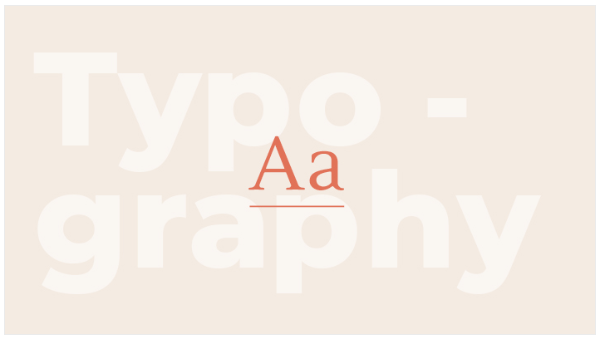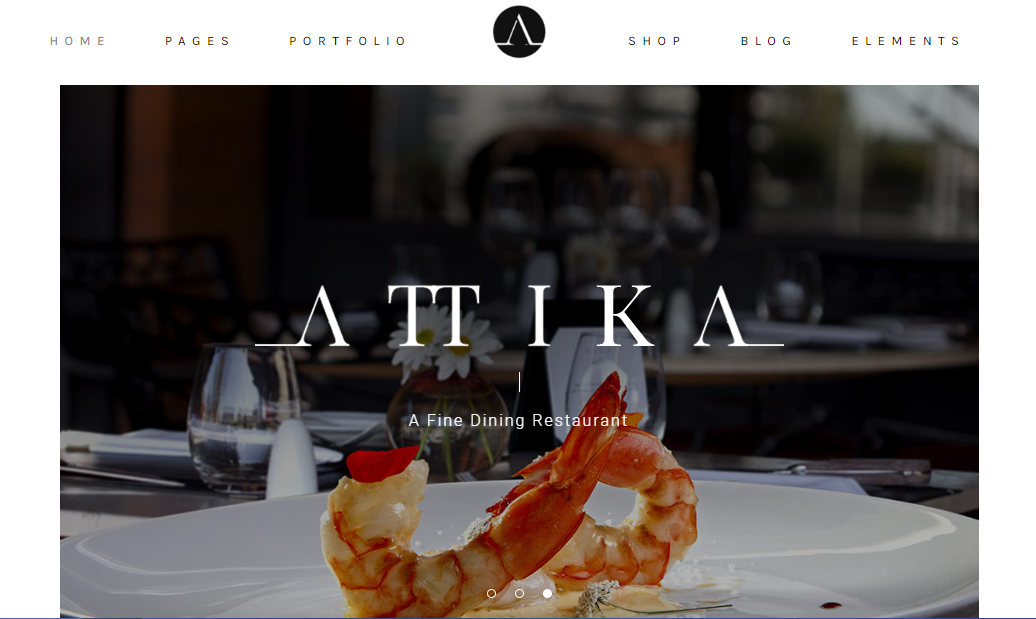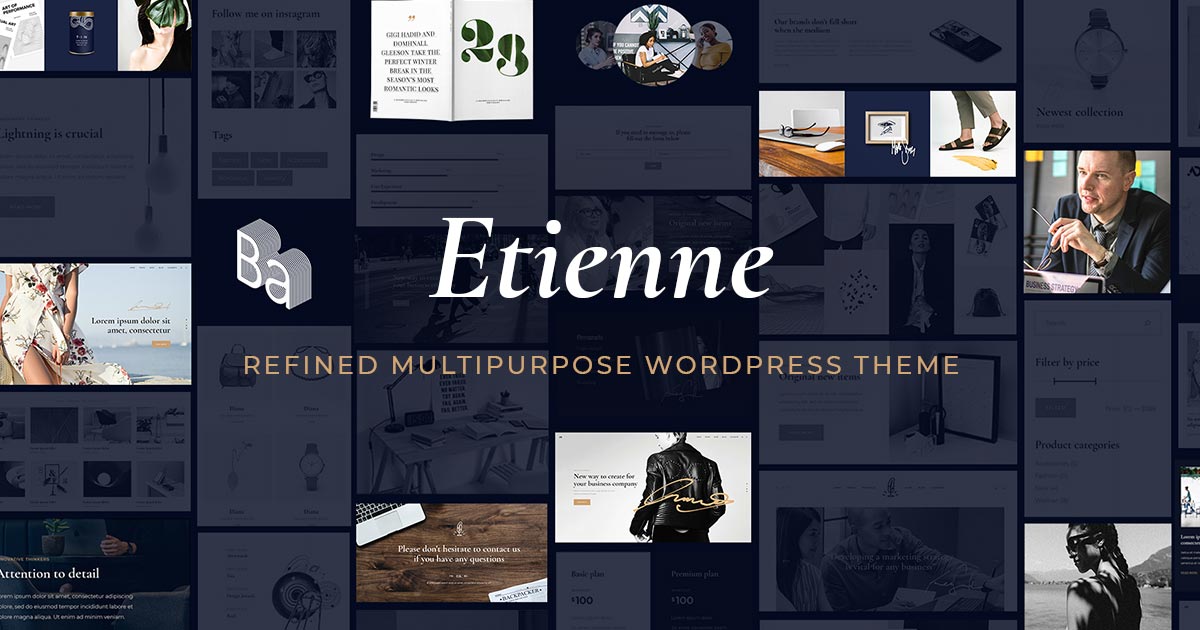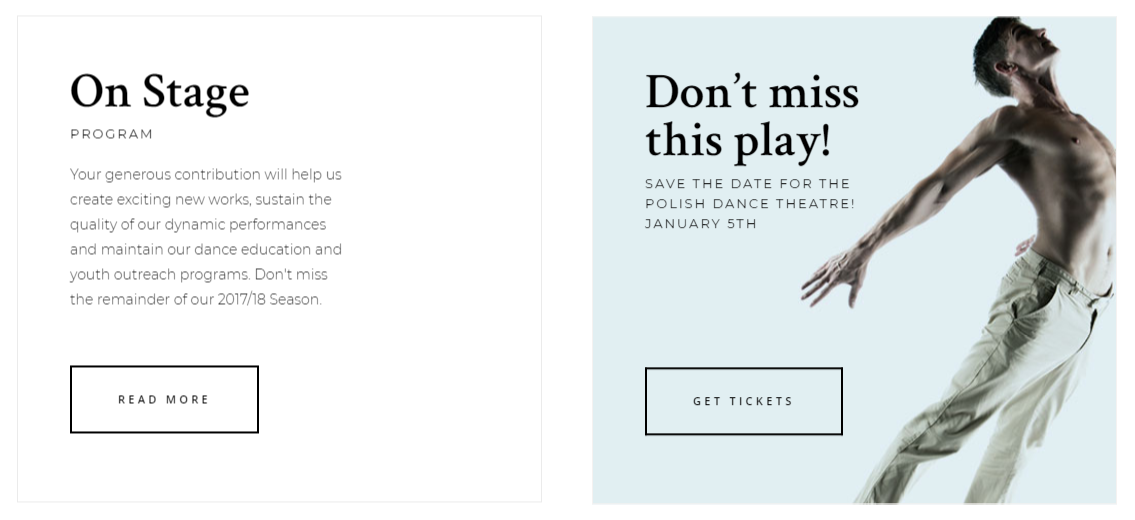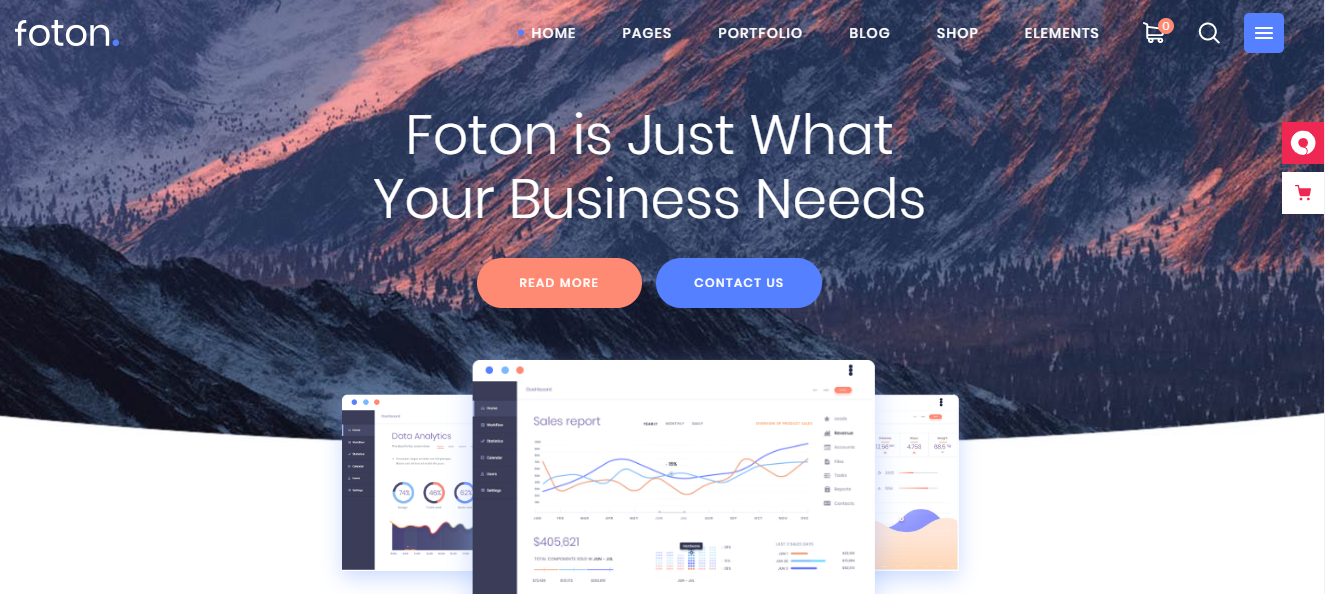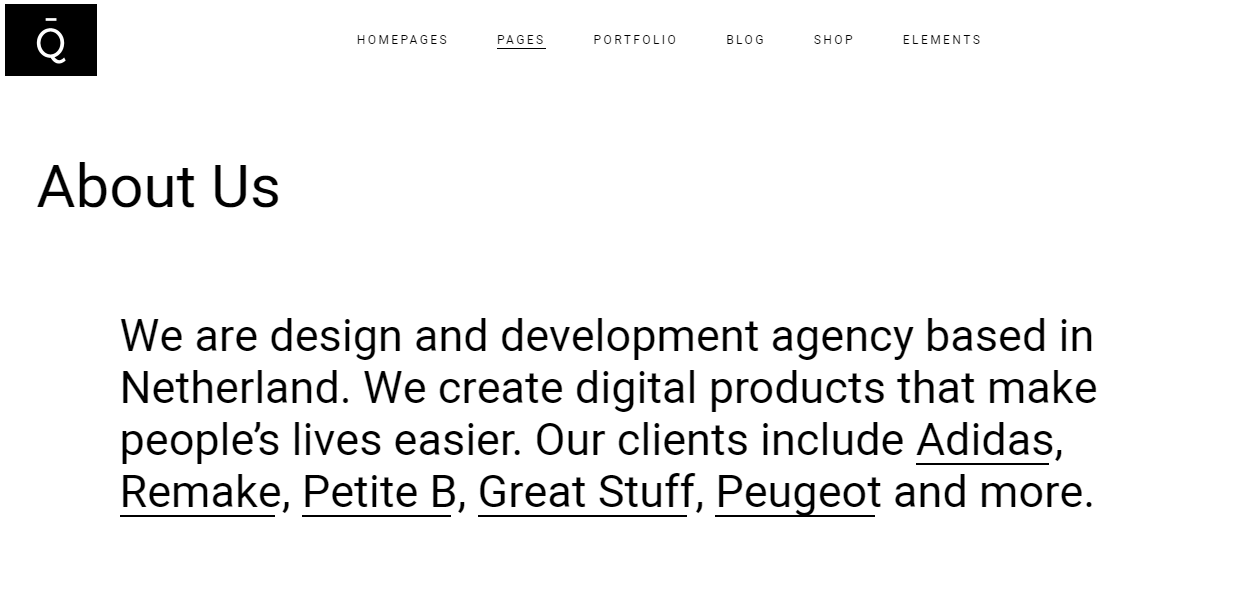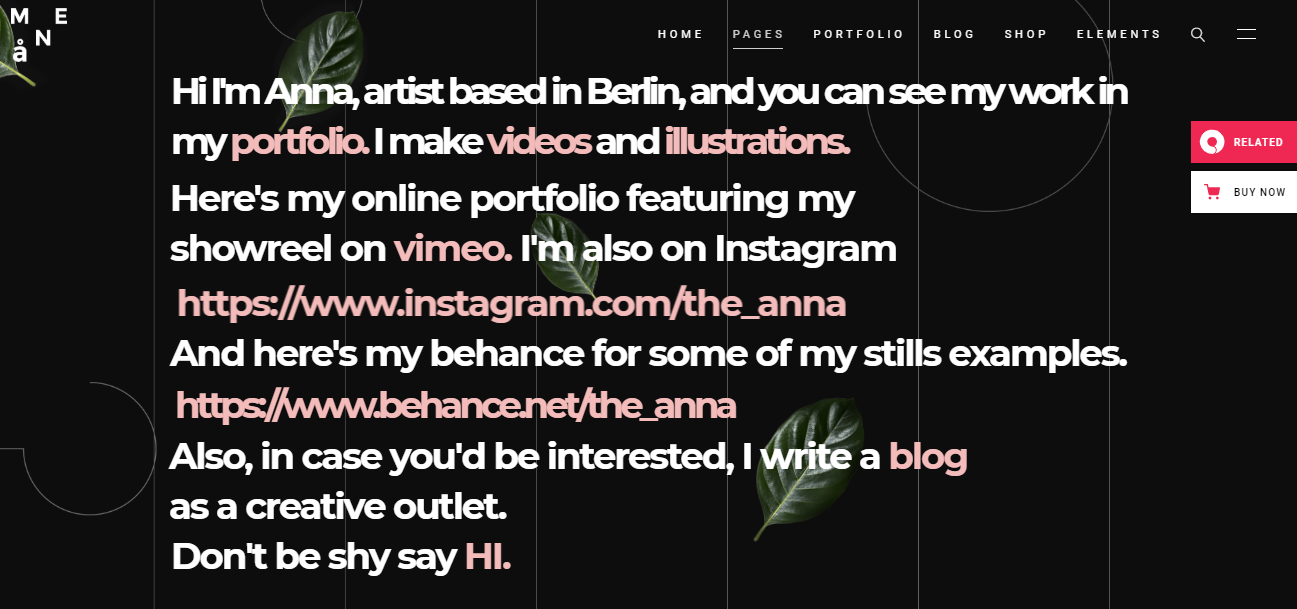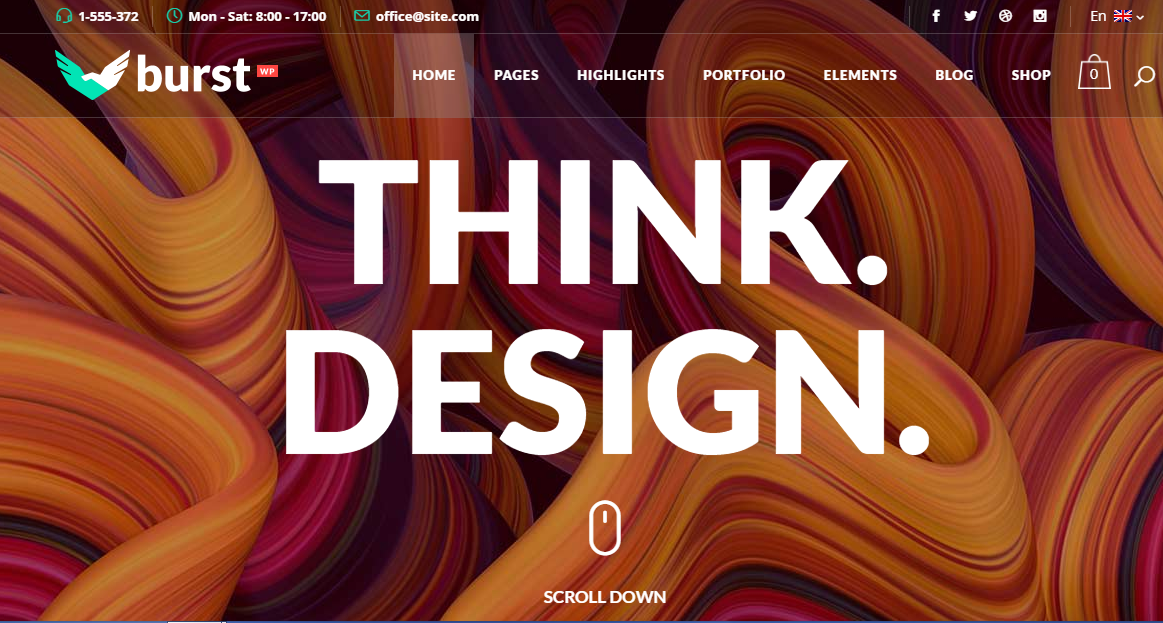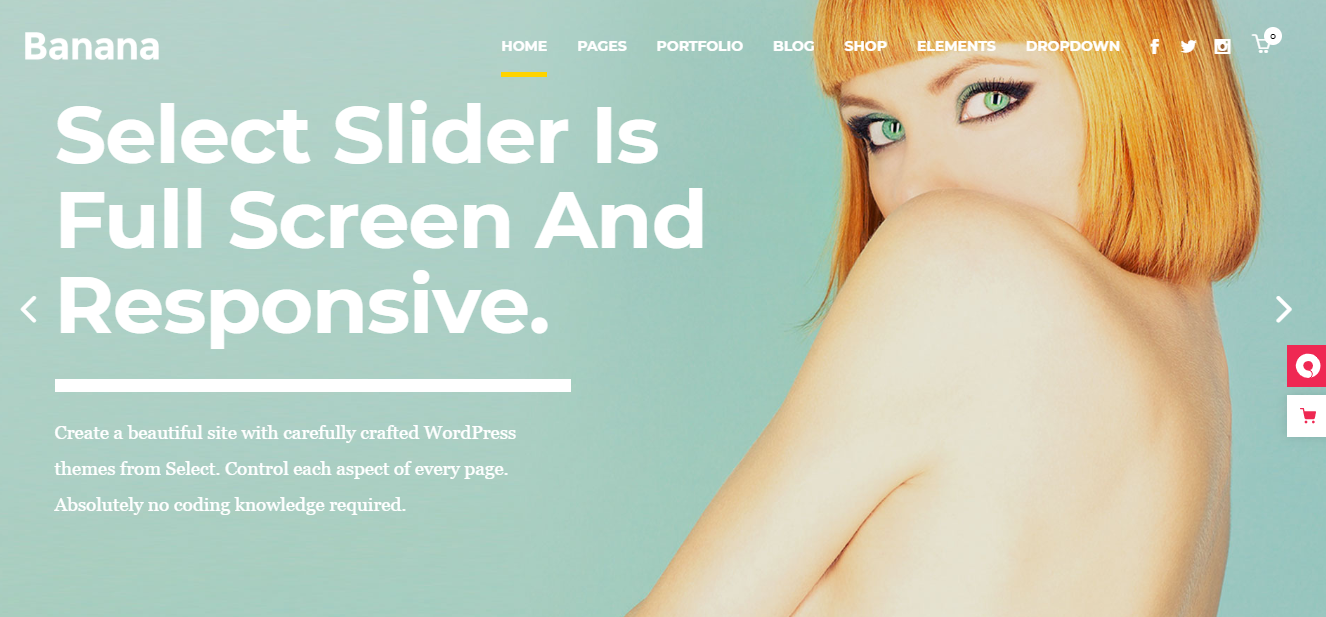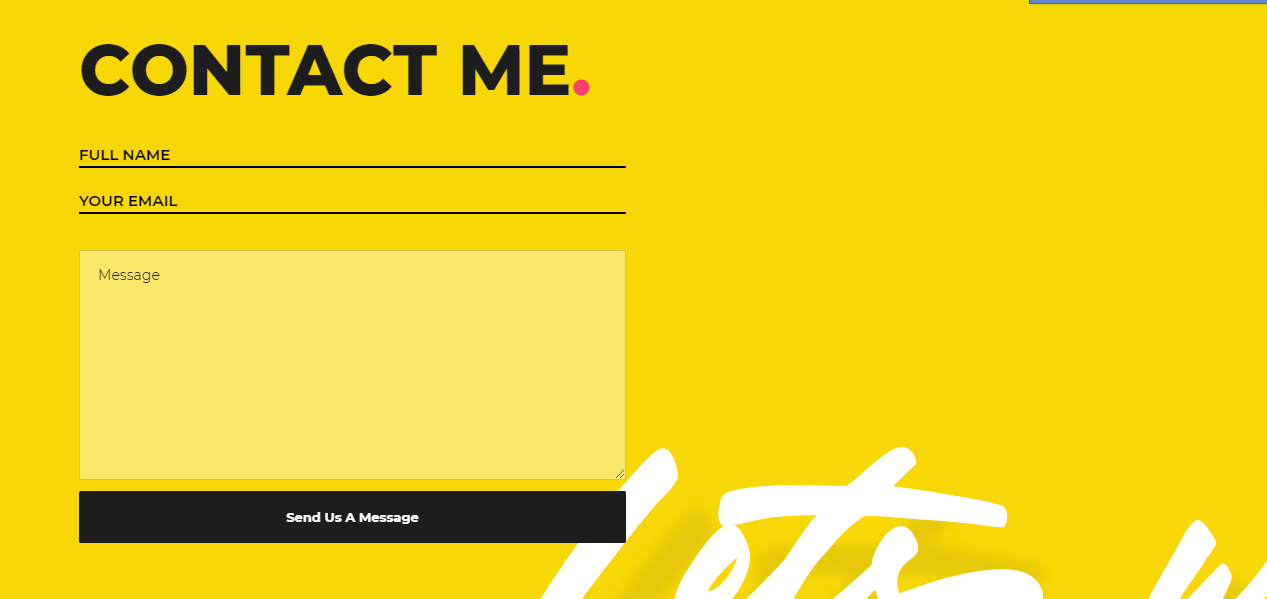
6 mẹo lựa chọn font chữ cho thiết kế website hoàn hảo năm 2024
Lựa chọn font chữ cho thiết kế website ấn tượng chưa bao giờ là dễ dàng. Lựa chọn font chữ là yếu tố quyết định tới tính thẩm mỹ của một thiết kế website. Nếu bạn đang gặp khó khăn trong việc thiết kế website, hãy tham khảo 6 mẹo lựa chọn font chữ cho thiết kế website hoàn hảo cùng Bee Art nhé!
Thiết kế website là một quá trình dài hơi cần bỏ ra nhiều công sức. Bạn phải cân nhắc nhiều yếu tố, từ cách phối màu đến xác định vị trí logo, bố cục và thiết kế nội dung văn bản. Có lẽ phần khó khăn nhất khi thiết kế website chính là làm cách nào để phối hợp thật tốt tất cả các yếu tố này nhằm tạo ra sản phẩm hoàn chỉnh, hợp lý và cân bằng.
Lựa chọn font chữ cho thiết kế website ấn tượng chưa bao giờ là dễ dàng
Font chữ là một phần quan trọng trong việc tạo nhất khối thống nhất ấy. Một khi đã có ấn tượng chung cho website của bạn, người xem sẽ tập trung kĩ hơn vào phần nội dung văn bản để tìm hiểu thêm về bạn cũng như thương hiệu. Đó là lý do vì sao việc chú ý đến thiết kế font chữ là vô cùng quan trọng khi bạn muốn liên kết những yếu tố thiết kế này lại với nhau. Điều này có nghĩa là typeface mà bạn chọn phải dễ đọc, gọn gàng và có sức thu hút vừa phải để các yếu tố khác không bị lu mờ.
Lựa chọn phông chữ đúng đắn là yếu tố quyết định để có một thiết kế website tốt, dù cho trang web của bạn là portfolio, trang blog, cửa hàng online hoặc website của tập đoàn lớn. Nhằm giúp bạn tìm ra phông chữ phù hợp với tinh thần của thương hiệu, chúng tôi đã tinh giản quá trình khó khăn này. Dưới đây là một vài yếu tố mà bạn nên cân nhắc khi chọn phông chữ cho thiết kế website của mình.
Mẹo lựa chọn font chữ cho thiết kế website hoàn hảo
Thiết kế website không chỉ là việc sắp xếp hình ảnh và màu sắc mà còn bao gồm cả việc lựa chọn font chữ phù hợp. Font chữ đóng vai trò quan trọng trong việc truyền tải thông điệp, tạo ra sự nhất quán và thẩm mỹ cho trang web. Để giúp bạn lựa chọn font chữ hoàn hảo cho website của mình trong năm 2024, dưới đây là 6 mẹo quan trọng:
Lựa chọn những font chữ cơ bản khi thiết kế website
Khi nhắc đến phông chữ cho trang web, có rất nhiều thứ cần phải nghiên cứu và có thể bạn sẽ trở nên quá tải. Đó là lý do vì sao chúng ta nên bắt đầu với những thứ cơ bản nhất trước khi tiến xa hơn.
• Thử qua các phông chữ có hoặc không có chân (Serif hoặc Sans): đây là một yếu tố cơ bản trong việc phân loại phông chữ. Theo bảng chữ cái La Mã, các họ phông chữ Serif thường có một đường kẻ ở cuối mỗi kí tự theo chiều ngang hoặc dọc.
Một vài phông chữ thuộc họ này bao gồm Times New Roman và Georgia. Phông chữ Time New Roman được xem là lựa chọn an toàn cho thiết kế trang web. Nhìn chung thì bạn khó mà làm hỏng mọi thứ với phông chữ vô cùng cơ bản này vì nó rất dễ đọc. Bên cạnh đó nó cũng xuất hiện từ rất lâu nên nhiều người dùng đã quá quen với nó. Nếu muốn nổi bật hơn thì chúng tôi đề nghị bạn xem qua bộ sưu tập phông chữ Noe Display, Freight Text hay Portrait. Dĩ nhiên là bạn cũng có thể sử dụng các phông chữ có chân của Google như Playfair Display, Cormorant Garamond, hoặc Crimson Text.
Lựa chọn những font chữ cơ bản khi thiết kế website
Những typeface Sans không có chi tiết “chân” ở các kí tự và được coi là mang tinh thần thiết kế hiện đại và gọn gàng hơn khi so sánh với các bộ phông chữ có chân. Helvetica, Tahoma, Verdana, Futura, và Arial là những ví dụ điển hình cho loại phông chữ này. Nếu không muốn tốn chi phí, chúng tôi đề nghị bạn thử qua phông chữ của Google như Roboto, Source Sans Pro, Poppins, Heebo, và Montserrat.
Lựa chọn những font chữ cơ bản khi thiết kế website
Quyết định lựa chọn phông chữ phần lớn phụ thuộc vào đối tượng người xem và cảm giác bạn muốn mang lại khi họ sử dụng nó. Nhìn chung, phông chữ có chân được sử dụng nhằm cho thấy sự lịch thiệp và trang trọng. Dù vậy chúng cũng được sử dụng để mang đến diện mạo mới cho trang web, đồng thời phông chữ có chân cũng xuất hiện trong lĩnh vực tạp chí và thời trang.
Phông chữ không có chân thể hiện sự đơn giản và trực tiếp. Tuy nhiên, một trong những đặc điểm nổi bật của phông chữ không chân là chúng vô cùng linh hoạt. Ví dụ, nếu được so sánh với typeface cũ thì phông chữ không chân mang có thể tỏa sáng với cá tính riêng và đồng thời thể hiện giá trị truyền thống.
• Kerning, leading và tracking: Đây là 3 yếu tố thiết kế quan trọng liên quan đến diện mạo của typeface. Những phương pháp này tác động trực tiếp đến khoảng cách giữa các kí tự, từ đó góp phần tạo nên một sản phẩm dễ đọc và ưa nhìn. Kerning là khoảng cách giữa 2 kí tự, leading đại diện cho khoảng cách giữa các dòng văn bản và tracking (hay còn gọi là letter-spacing) là khoảng cách giữa các nhóm kí tự.